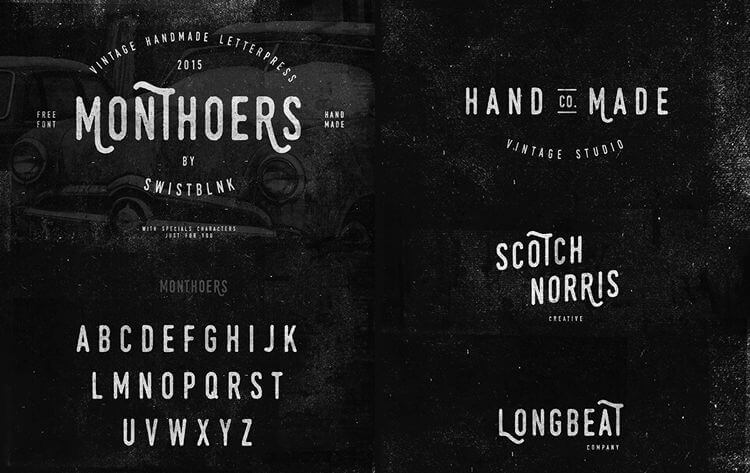
Bough Hand-Drawn Typeface等手書き風フォント24選!サイトに魅力的な個性と温かいタッチを加えよう
Web作品に魅力と個性的なタッチを加えたい場合には、手書きフォントが最適。
ホワイトスペースにうまく使えば、デザインに付加価値的なスタイルを与えてくれます。
本記事では、無料で使える手書きフォントの最新コレクションをご紹介します。24種類含まれていますので、きっと気に入るものが見つかるでしょう。
1.Carosello Font
Carosello free handwritten Font
2.Arabella Free Font
Arabella free handwritten Font
3.Waterlily Free Handwriting Font
Waterlily free handwritten Handwriting Font
4.Breathe Font Family
free handwritten Breathe Font Family
5.MAZAK Font
MAZAK Font family handwritten
6.Nickainley Handwriting Font
free Nickainley Handwriting Font
7.Cutepunk Typeface – Light, Regular & Bold – By Cutepunk (OTF)
free font Cutepunk Typeface
8.Barokah Uppercase & Lowercase Display By Graptail Design (OTF)
Barokah Uppercase font free Lowercase Display
9.El Capitan Hand-Drawn Font By Petr Knoll (OTF & AI)
El Capitan Hand-Drawn free Font
10.Sweet Pineapple Hand-Drawn Serif By Medialoot (OTF & Web Font)
Sweet Pineapple Hand-Drawn free Serif
11.Mathlete Hand-Drawn Font – Skinny, Slant, Bulky & Bulky Slant – By Mattox (OTF & Web Font)
Mathlete free Hand-Drawn Font
12.ALDI Handwritten Sans-Serif – Regular & Bold – By Phil Goodwin (OTF)
ALDI Handwritten free Sans-Serif
13.Handmade Hipster Font Bellaboo By Marcelo Reis Melo (OTF)
Handmade Hipster Font free
14.Liberal Hand Serif Font – Regular & Bold – By Tom Chalky (OTF & TTF)
Liberal Hand Serif Free Font
15.Barry Font Bold – By Eduardo Higareda (OTF & TTF)
Barry Free handwritten Font Bold
16.Bough Hand-Drawn Typeface By Pavel Korzhenko (OTF)
Bough Hand-Drawn Typeface free font
17.Fabfelt Handwritten Script – Bold – By Despinoy Fabien (OTF & Web Font)
Fabfelt Handwritten Script free font
18.SUNN Uppercase Handwriting Font By Rit Creative
SUNN Uppercase Handwriting Font free
19.FFAD Matro Handwritten Font By SuperBruut (TTF & Web Font)
FFAD Matro Handwritten free Font
20.Dilem Handwritten Uppercase Display Typeface By Dilem Akiner (TTF)
Dilem Handwritten Uppercase Display free font Typeface
21.Handkerchief Font By Joe Chau (TTF)
Handkerchief free handwritten Font
22.CABANA Handmade Font By Adrien Coquet (OTF)
CABANA Handmade free Font
23.Thirsty Dog Handdrawn Typeface By Simon Stratford (OTF)
Thirsty Dog Handdrawn free Typeface
24.Monthoers Handmade Letterpress By Agga Swist’blnk (TTF)
Monthoers Handmade free font Letterpress